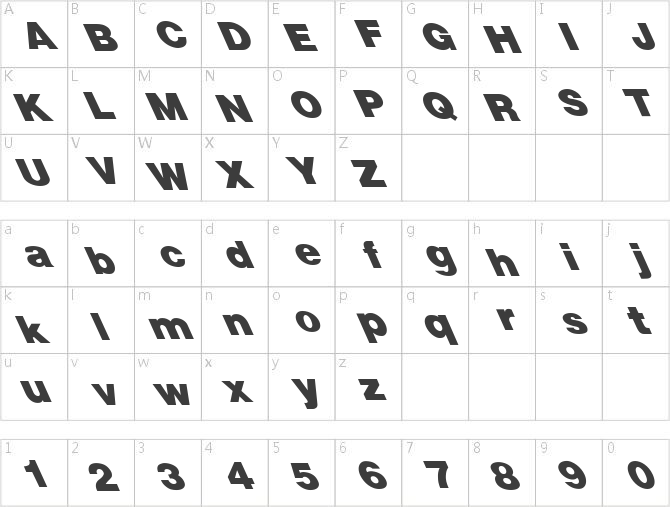
FZ BASIC 13 LEFTY 詳情頁(yè)
FZ BASIC 13 LEFTY字體字庫(kù)是一款讓人賞心悅目、百看不厭的英文字體,適合各類廣告和產(chǎn)品包裝設(shè)計(jì)應(yīng)用,字體大小0.04MB,格式為ttf字體,上傳用戶是13226568769,作者/版權(quán)方為未知